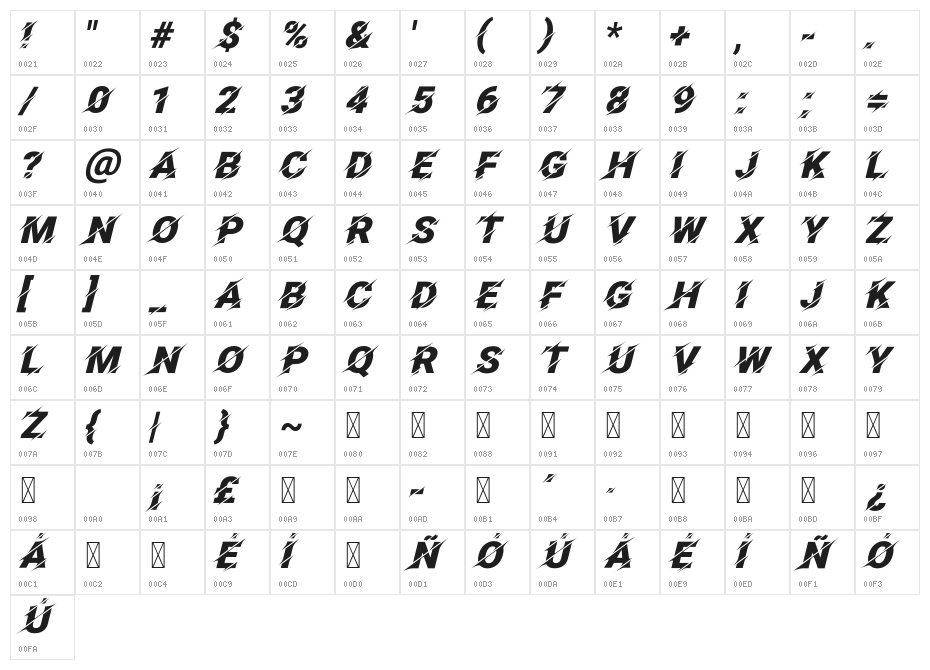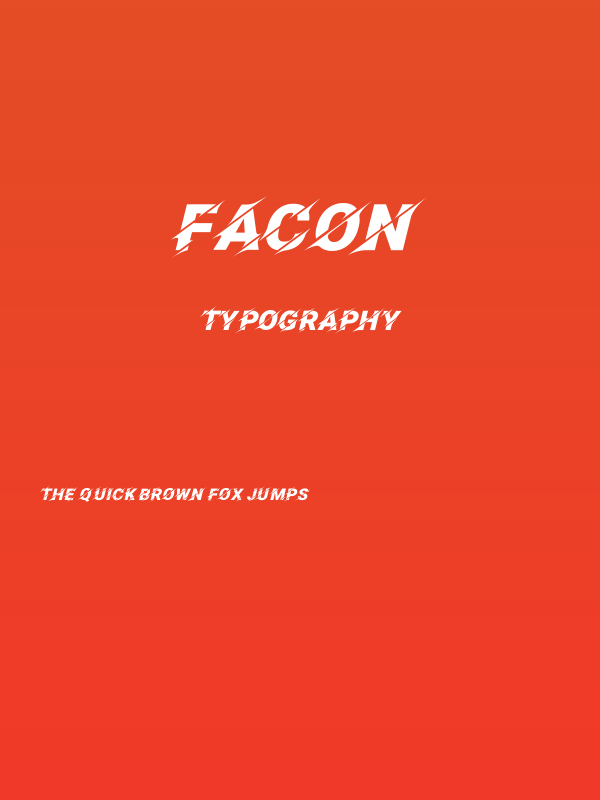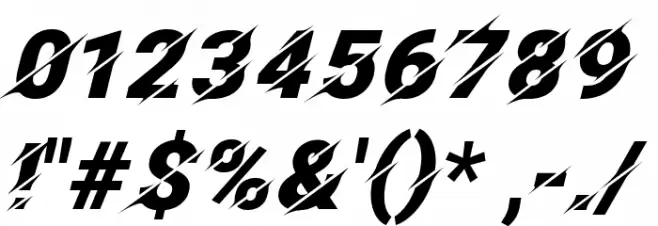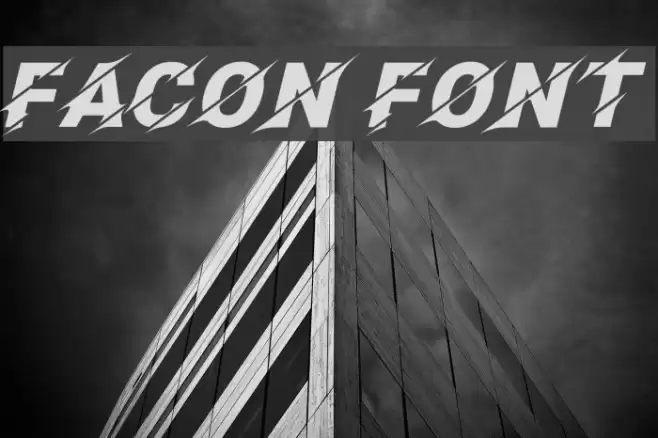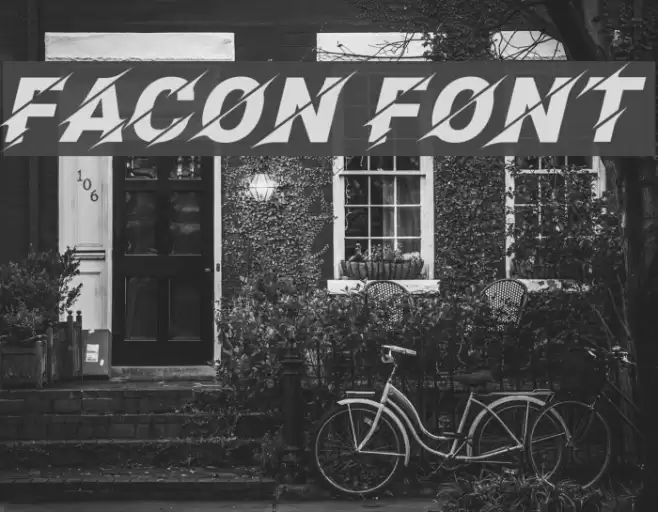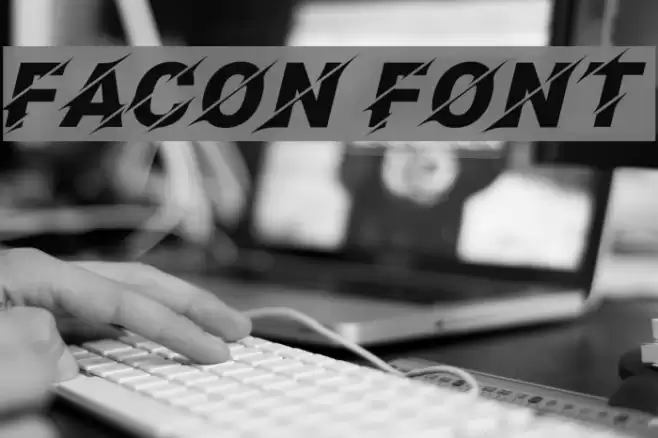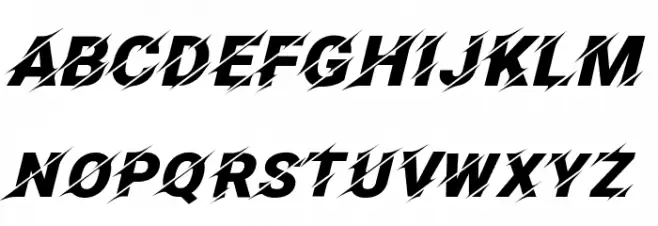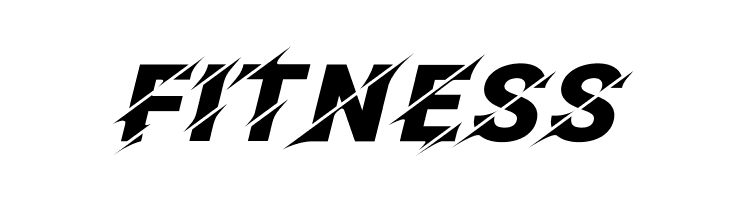
Facon Font
Facón
| Stil general | Modern, Energetic, Dynamic |
| Proiecte propuse | Perfect for sports branding, music album covers, action movie posters, or any project needing a bold, energetic typeface. |